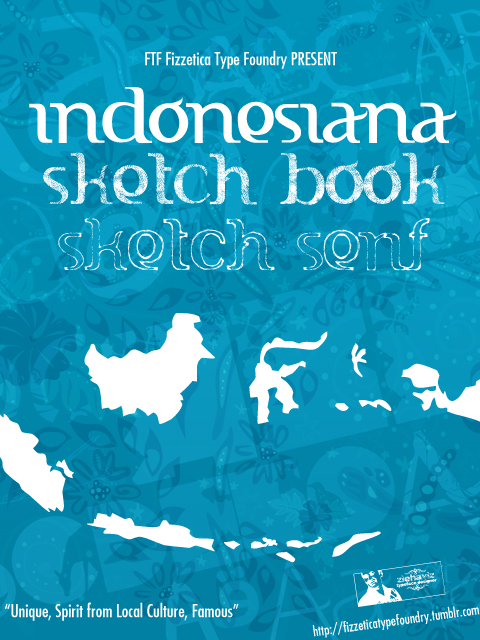
Categories | Foreign look, Various |
-INDONESIA- Suatu kebanggaan bagi Fizz-Labz dan FTF merangkai huruf ini menjadi alfabet utuh dari a-z "lowerchase" dari logo pariwisata Visit Indonesia 2009, font ini bersifat free (free font) yang hanya boleh dipakai untuk pribadi, pendidikan dan bukan untuk kepentingan komersil. -ENGLISH- These fonts are free (free fonts) which should only be used for personal and not for commercial purposes. More info for commercial use ONLY: fizzlabz@gmail.com |or Ph: +62 878 328 543 81 Or BUY here (PRO VERSION - Commercial Use): sellfy.com/p/K5Zd/ - HARGAI HAK CIPTA TYPE DESIGNER INDONESIA- ======================================================= Use without permission will be subject to more payments (amounting to approximately 20x the normal price). Penggunaan tanpa ijin akan dikenakan pembayaran lebih banyak (sebesar kurang lebih 20x dari harga normal). ======================================================= Fizzetica DepokAsiana TypeFoundry https://sellfy.com/fizzetica.co | Blog: http://fizzeticatypefoundry.tumblr.com Read our EULA (Commercial use) for this font: http://bit.ly/EULAFTF2015 |